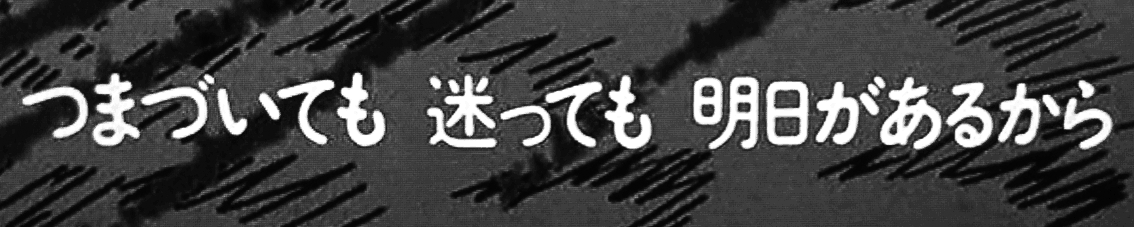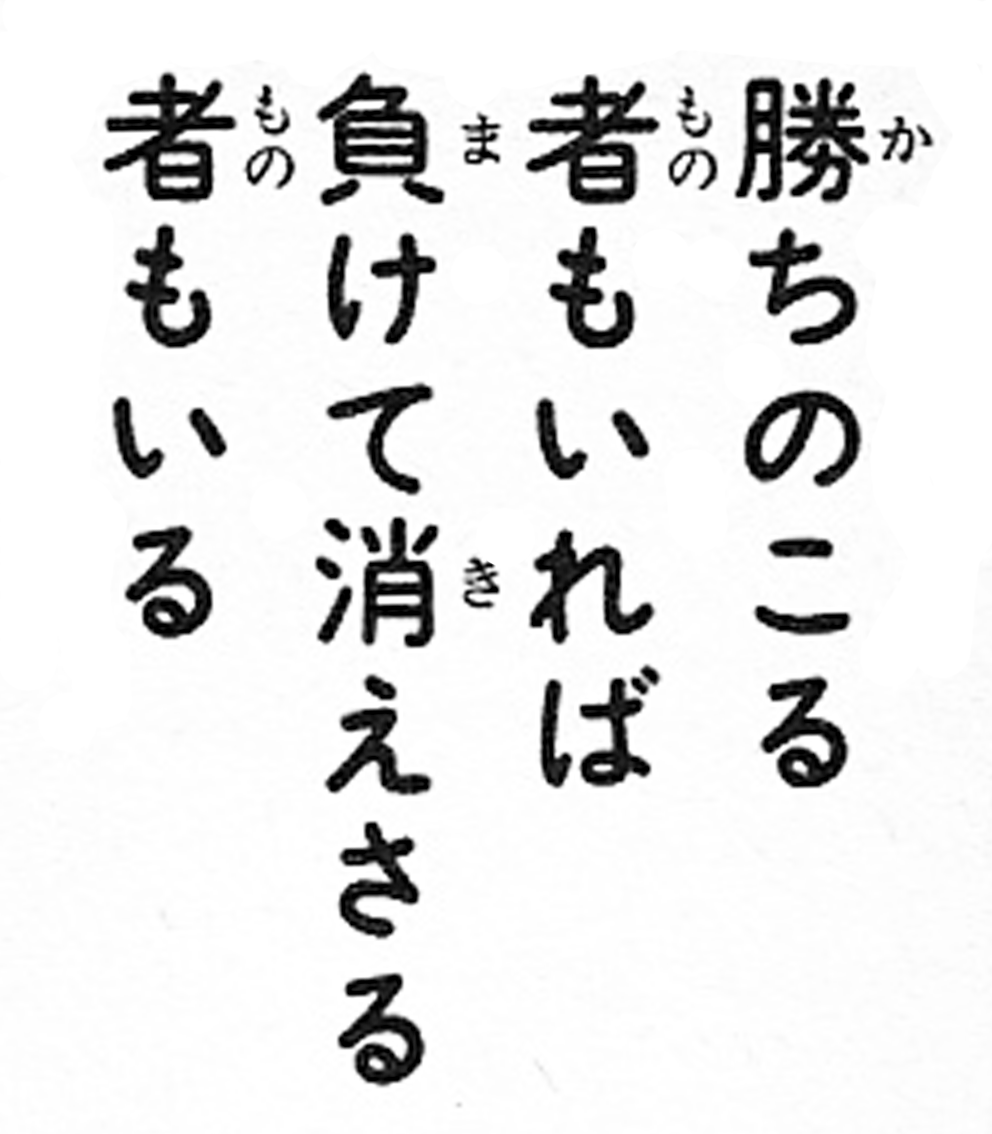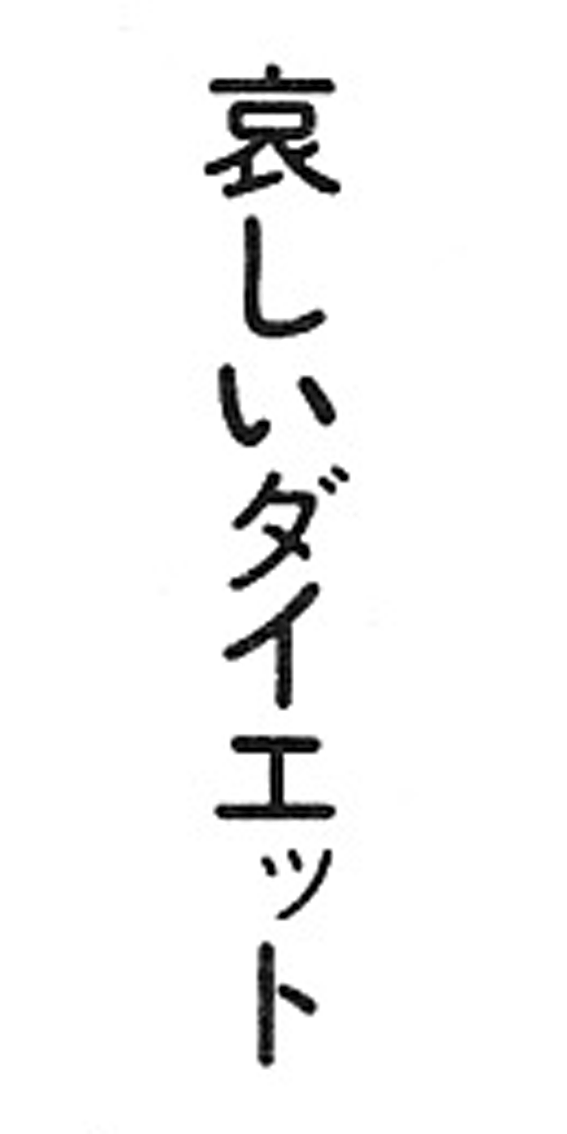
石井太丸ゴシック
最近、テレビをつけたら『ふしぎの海のナディア』のデジタルリマスター版再放送をやっていた。夕方で、家のなかには他に誰もいなくて、台所からごはんの炊ける匂いがしていた。
そうだ、子供のころ、ナディアになりたくて、生まれて初めて近所の美容室で髪を切ったら、ただのオカッパ頭にされて愕然としたっけ。そんな、あまり思いだしたくもないことをぼんやり思いだしていたら、エンドロールの字幕スーパーにはっとした。思わず目で追ったけれど、文字は絵の雲や風と一緒にどんどん流れていってしまった。
〈石井太丸ゴシック〉は、私が毎週金曜日の夜を心待ちにしていた当時、テレビ番組のテロップでよくつかわれていた書体だ。
テレビの画面でみたのと、紙の本でみたのと、どちらが先だったのかは思いだせない。そのころすでに特別な感情を抱いていたわけでもない。
でも大人になって、この書体を改めてみると、小さな宝物を贈られたみたいに、どきっとするのはどうしてなのだろう。
「時間」というのは不思議なものだなと思う。ありふれた、ふつうのものを、美しくする。
一般的には「レトロ」と表現するのかもしれない。
レトロ。
その言葉の使われ方にはおそろしく違和感があるのに、どうしても感傷がまじってしまう。
そのせいか、私が出会ったなかで、この書体が好きですというひとはいつも、ちょっと照れくさそうな、不本意のような顔をする。かつて純粋な部活少年だったことを白状するみたいに。
いわゆる「丸ゴシック」と呼ばれる、角が丸い、やさしい雰囲気をもったゴシック体なら、デジタルフォントでも選べないほどたくさん出ているけれど、1958年生まれの写植書体〈石井太丸ゴシック〉の個性は今でも唯一無二だと思う。
意識して輪郭を丸くしたというより、自然に角がとれたような丸み。「摩耗」したような角、とかくのは、いくら読者の勝手な印象とはいえ、それは言い過ぎだろうか。
ひとつひとつの文字をみても主張があるようには思われないのに、くっついてかたまりになったとたん、他のどれにも似ていない印象になる。
どういうことかというと、この文字でかかれた言葉は、かすかに甘い、半透明の膜でコーティングされているみたいに感じるのだ。淡い虹のように、不幸ではないけれどかなしい。ちょっと儚い甘さ。
そのイメージと直接関係があるのかはわからないけれど、この書体でかかれていたことを今でも憶えているのは、エッツの『もりのなか』という絵本である。
森へでかけた少年が、散歩の途中でさまざまな動物と出会い、ライオンや、象や、くまを次々となかまにしていく。
いかにも絵本的な繰り返し構造なのだが、ページの先にあらわれる同じ構図と、たんたんとした文章のリズムとが相まって、なんともいえず安心で、豊かな気持ちになる。
一度にたくさんは読みづらく感じるところもいい。
この絵本の最後は、動物たちとかくれんぼうをしているときに父親が迎えに来て、家に帰らなければならなくなった少年の、こんな言葉で終わる。
「みんな、まっててね。またこんど、さんぽにきたとき、さがすからね!」
読み返して初めて、気がついた。
あのころ、私の目には、この一行が、終わりの始まりを告げるエンドロールのようにみえていた。